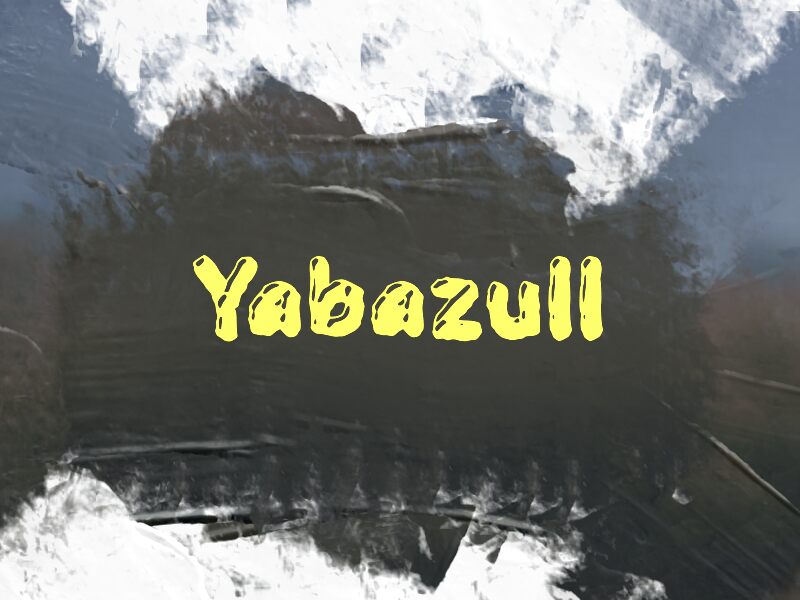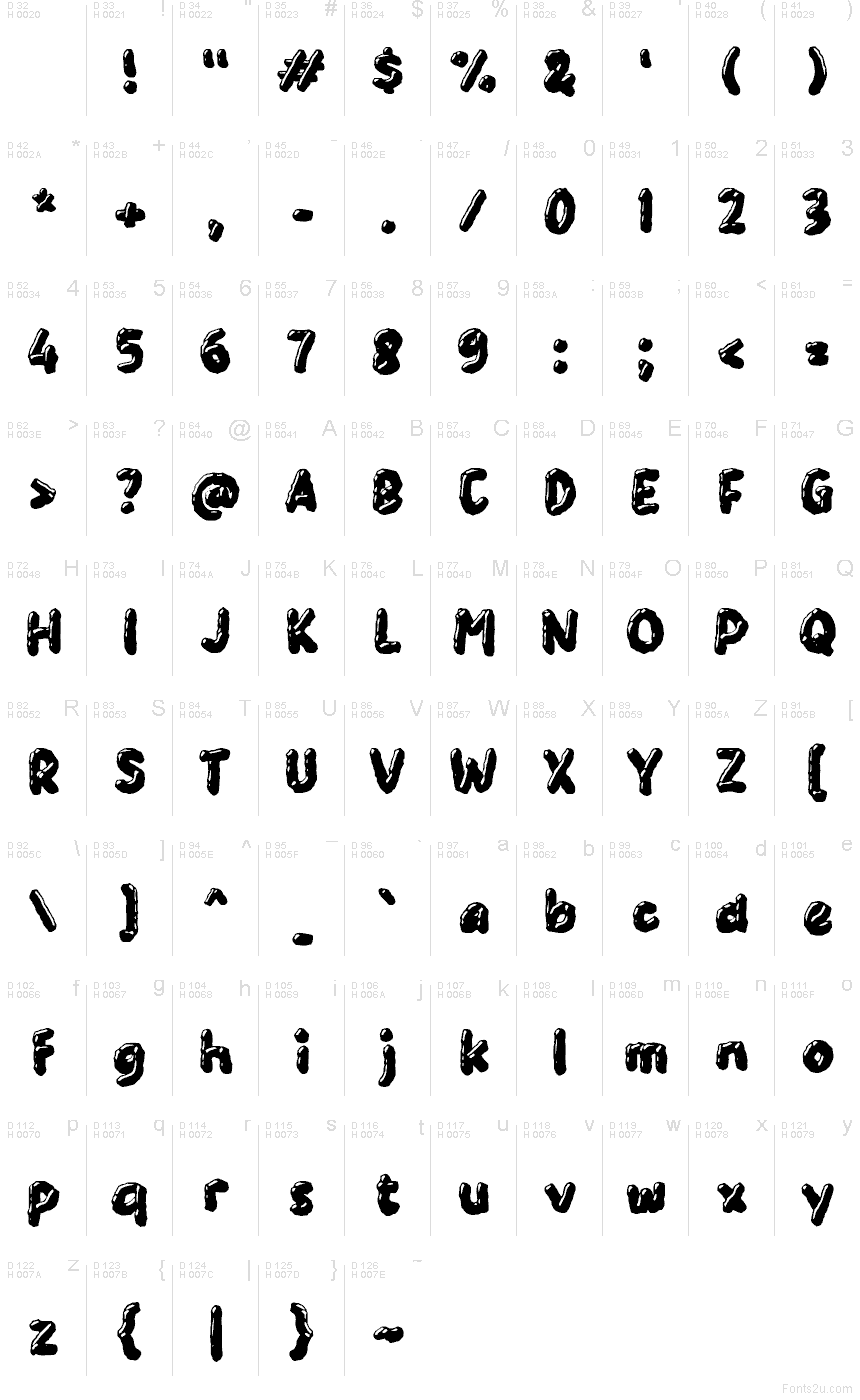
Yabazull
Yabazull da Wep é uma fonte decorativa gratuita com formas que lembram bolhas negras inchadas. Com curvas arredondadas e destaques brilhantes, as letras parecem úmidas e infladas. Essa textura lustrosa, quase como piche, percorre todo o design, conferindo um ar de terror de desenho animado sem cair no clichê das fontes de monstro excessivamente rígidas.
É perfeita para flyers de Halloween, convites de festas temáticas, títulos de jogos, designs de adesivos e embalagens criativas. Sua silhueta volumosa e superfície escorregadia dão às palavras curtas um forte impacto gráfico, sendo ideal para cartazes, cabeçalhos de stream ou posts em redes sociais que pedem um título grudento e divertido, fugindo do óbvio das fontes display tradicionais.